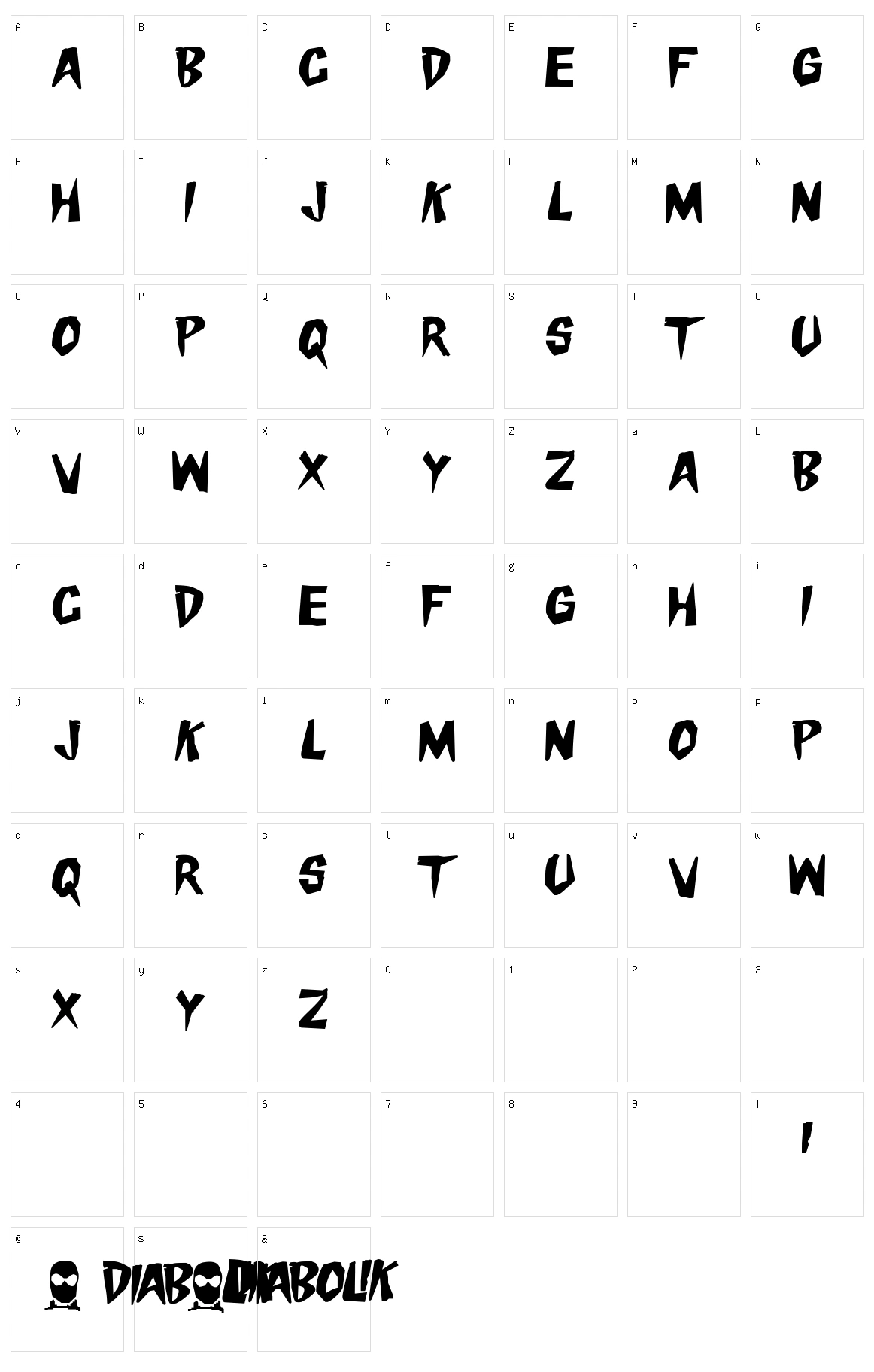
Font name: DANGER DIABOLIK Font (FontCOMICS Collection) - Latin Decorative font (versione 1.0)
Type designer: P. A. Vannucci
DANGER DIABOLIK font: direttamente dal film diretto da MARIO BAVA e interpretato da JOHN PHILLIP LAW, il font inedito per tutti
gli estimatori del film. Da notare il ritocco necessario in Photoshop per conferire, alla titolazione, l'originale bordatura.
DANGER DIABOLIK font: directly from the Best movie by MARIO BAVA, with JOHN PHILLIP LAW,
the original font for all lovers. Use ADOBE Photoshop for the original border from title.